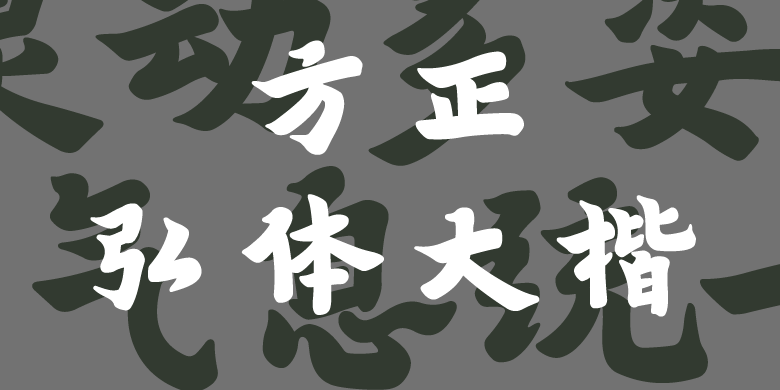
方正弘体大楷
张文一,郭毓海
楷书、常规书写·毛笔
该字体是第十二届“方正奖”专业组铜奖作品,原名《鸿鹄楹联》,源于弘一法师(李叔同)于1929年到1932年间所书部分楹联的楷书式样。该字体有魏碑的味道而改方折为圆浑,间杂少量行、草结构,灵动多姿,气息统一。评委汪文评价其:“圆润中透出禅意,温柔中彰显力度。笔画圆融有力,结构松紧适中,体现了作者对于弘一书法的钻研和执着。”